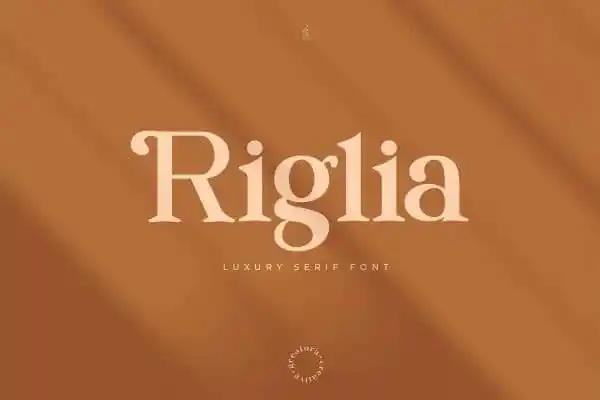
Riglia Serif Font – Download Grátis
Riglia Serif é uma fonte criada por Greafora Creative com um estilo de tipo serif bold que transmite uma impressão clássica e vintage. Suas linhas sóbrias são perfeitas para projetos que valorizam elegância, como logos elaborados, cartões de casamento, convites e identidades de marcas. A fonte também oferece um toque refinado aos títulos em suas folhas de trabalho e projetos, com a adição de uma leve remoção na posição alternativa dos caracteres. Este estilo elegante faz dela uma escolha ideal para designers propondo estilos sofisticados que são tão belos quanto funcionais. Não hesite em explorar as possibilidades criativas de Riglia Serif ao criar designs memoráveis e impecavelmente bem projetados.